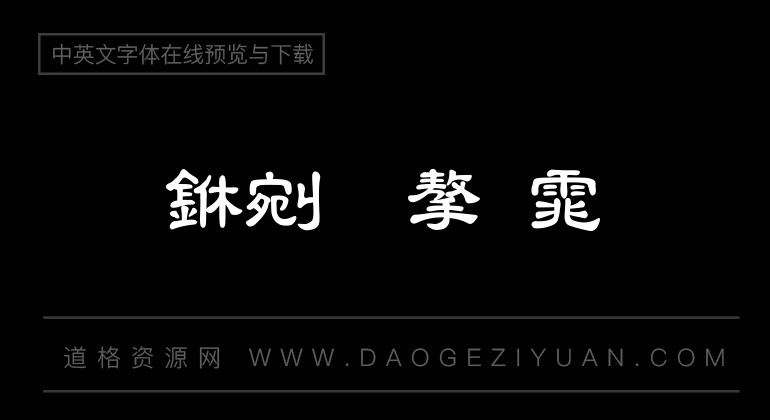
超研泽粗隶
? 超研泽粗隶字体是一款中文粗体字体,由超研科技开发,总计有五种字重,分别为常规、细体、粗体、极粗、极细。每种字重都带有繁体和简体,共计十种字体。超研泽粗隶字体具有清晰的结构,笔画粗细适中,字形简洁大方,极具古典气质,可以满足不同需求的文字排版。
超研泽粗隶是一款非常不错的手写艺术字体,具有很好的视觉感,适合于文化类的宣传设计、商业类品牌的广告和产品包装设计以及个性化文字排版等较多场景。